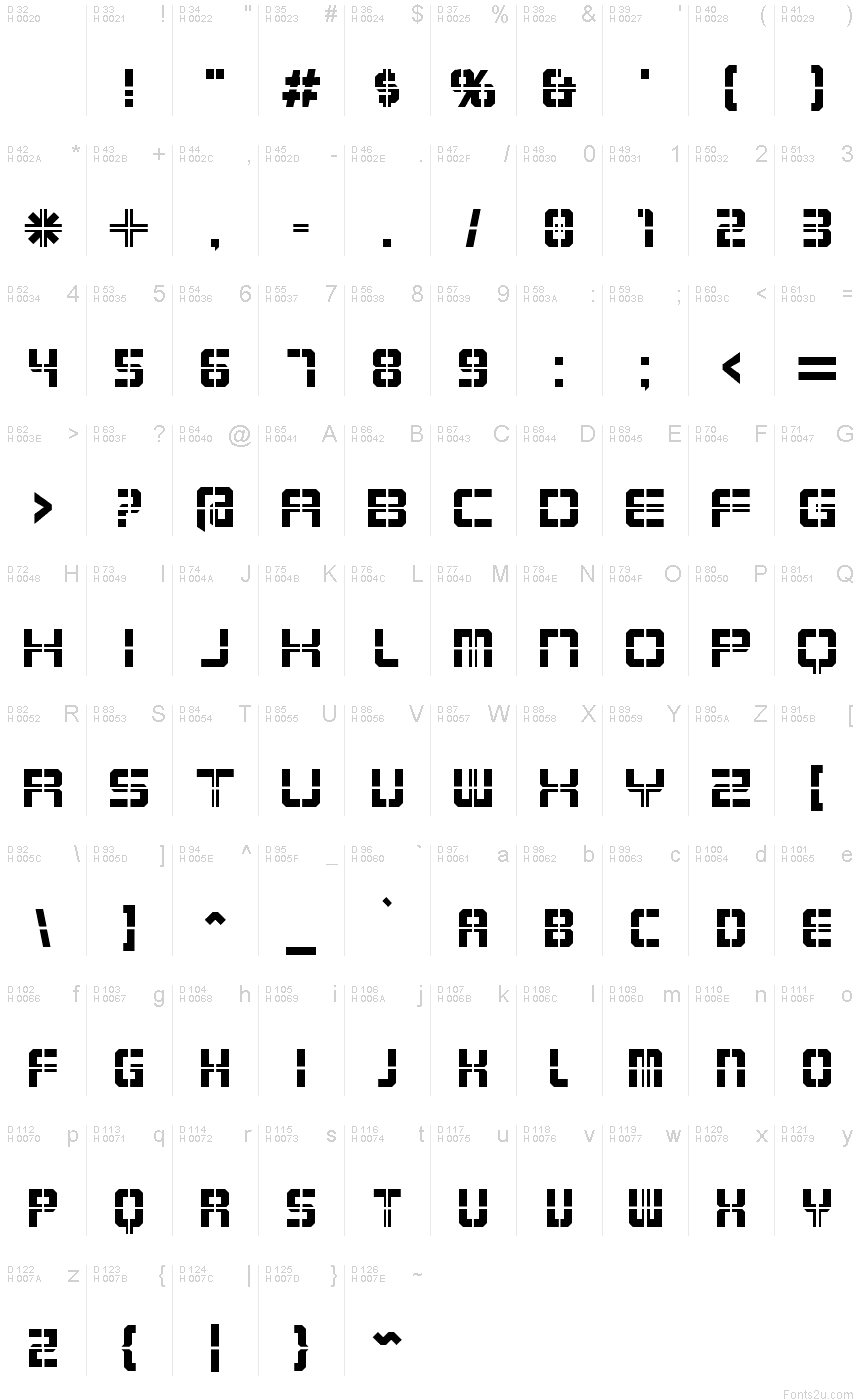
Karnivore Krate von Apostrophic Lab ist eine kostenlose, techno-digitale Schriftart. Die Lettern bestehen aus massiven, schwarzen Blöcken, die durch feine horizontale Einschnitte unterbrochen werden – das lässt jedes Wort wie einen Barcode oder gestapelte Frachtcontainer wirken. Der Rhythmus ist starr und mechanisch; die scharfen Ecken und quadratischen Punzen verleihen deinen Texten eine wuchtige, industrielle Präsenz auf Print oder Screen.
Mit Karnivore Krate erhältst du eine mutige, futuristische Stimme, die bei Game-Logos, Cyberpunk-Postern, Sci-Fi-Buchcovern, Musik-Artworks, Tech-Event-Flyern und Motion-Graphics-Titeln sofort ins Auge fällt. Diese kostenlose Schrift glänzt vor allem in großen Schriftgrößen, wo ihr geometrisches Muster perfekt zur Geltung kommt. Kombiniere sie für den Fließtext mit einer klaren Grotesk und überlasse Karnivore Krate die lauten, wirkungsvollen Headlines.